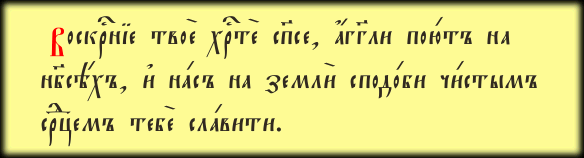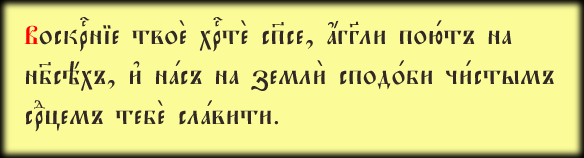
ЦЕРКОВНО-СЛАВЯНСКИЙ ШРИФТ «OSTROG»
Шрифт Ostrog
Гарнитура «Ostrog» — это живое дыхание истории, воссозданное по страницам редчайших изданий второй половины XVI века, выходивших в типографиях Вильно и Острога. Считается, что создателем этого величественного рисунка был сам Петр Мстиславец — выдающийся восточнославянский типограф и верный соратник первопечатника Ивана Фёдорова.
Этот шрифт воплощает в себе строгость и монументальность первопечатных книг, заложивших фундамент всей славянской книжной культуры. Использование гарнитуры «Ostrog» позволяет придать изданию особый статус, подчеркивая глубокую связь времен и верность древним традициям православного просвещения.
Шрифт эпохи первопечатников XVI века. Предположительное авторство Петра Мстиславца.
ЦЕРКОВНО-СЛАВЯНСКИЙ ШРИФТ «POCHAEVSK»
Шрифт Pochaevsk
Гарнитура «Pochaevsk» берет свое начало в богослужебных книгах прошлого столетия, выходивших из стен типографии Почаевской Лавры. За основу современной версии Pochaevsk Ucs была взята исторически точная цифровая копия, сохранившая все характерные особенности лаврского печатного стиля.
В истории создания этого шрифта упоминаются различные исследователи и дизайнеры, вложившие труд в его сохранение: Никита Симонс (1996), архиепископ Иоанн (1999) и представители Orthodox Information Data Associates. Благодаря их усилиям, сегодня мы имеем возможность использовать это наследие для создания текстов, пронизанных духом истинного церковного благочестия.
Историческая гарнитура Почаевской Лавры. Цифровая адаптация мастеров конца XX века.
ЦЕРКОВНО-СЛАВЯНСКИЙ ШРИФТ «POSAD»
Шрифт Posad
Шрифт «Posad» — это еще один выразительный декоративный инструмент, идеально подходящий для художественного оформления заголовков в церковных и исторических изданиях. По своему общему строю и духу он во многом напоминает гарнитуру «Zlatoust», однако обладает своими уникальными чертами, придающими ему особый колорит.
В отличие от более строгого начертания «Zlatoust», буквы «Посада» дополнены характерными засечками и изящными «узелками» на линиях. Эти детали делают рисунок более сложным и насыщенным, отсылая нас к традициям богатого рукописного оформления древнерусских книг, где каждый элемент текста нес на себе печать особого благолепия.
Декоративный заголовочный шрифт с засечками и узловыми элементами.
ЦЕРКОВНО-СЛАВЯНСКИЙ ШРИФТ «PSALTYR»
Шрифт Psaltyr
Шрифт «Psaltyr» — это цифровая адаптация одной из известных дореволюционных печатных гарнитур. Автором исходной компьютерной версии, созданной в 1994 году, является Никита Всесветский. Данный шрифт представляет собой достаточно точную копию своего исторического прообраза, сохраняя дух классического славянского книгопечатания.
При использовании стоит учитывать авторские особенности цифровой версии: буквы здесь вытянуты по вертикали примерно на 20–30% относительно печатного оригинала, а надстрочные знаки расположены более компактно. Несмотря на эти нюансы и некоторые упрощения в рисунке, «Psaltyr» остается востребованным инструментом для тех, кто ищет гармоничное сочетание традиции и цифровых стандартов.
Цифровая версия исторической гарнитуры. Автор — Н. Всесветский (1994).
ЦЕРКОВНО-СЛАВЯНСКИЙ ШРИФТ «SLAVJANIC»
Шрифт Slavjanic
Шрифт «Slavjanic» по своему рисунку близок к известной гарнитуре «Oglavie», однако обладает иными пропорциями и специфической контрастностью линий. Долгое время он оставался практически единственным доступным шрифтом такого типа в кодировке Ucs8, что обеспечило ему широкое распространение в цифровых церковных архивах прошлых лет.
Данная гарнитура выложена прежде всего в целях обеспечения технической совместимости. Мы рекомендуем использовать «Slavjanic» в тех случаях, когда у вас уже имеется готовый текст, сверстанный именно этим шрифтом. Для создания же новых трудов и качественной верстки предпочтительнее обращаться к более совершенной гарнитуре «Oglavie».
Шрифт для совместимости со старыми текстами (Ucs8). Аналог гарнитуры Oglavie.
ЦЕРКОВНО-СЛАВЯНСКИЙ ШРИФТ «STAROUSPENSKAYA»
Шрифт StaroUspenskaya
Гарнитура «StaroUspenskaya» была бережно воссоздана по страницам Псалтири издания Киево-Печерской лавры, предположительно середины XIX века. Она несет в себе те специфичные детали, которые делают узнаваемой любую лаврскую гарнитуру, выделяя её среди прочих богослужебных шрифтов того времени.
Несмотря на свое южное происхождение, рисунок этого шрифта оставляет впечатление удивительной суровости и аскетичной строгости. Его линии вызывают ассоциации с древними северными обителями — морозными Соловками или величественным Валаамом, что делает «Староуспенскую» гарнитуру идеальным выбором для изданий, требующих особого настроя и духовной сосредоточенности.
Киево-Печерская гарнитура XIX века. Характеризуется строгим и суровым рисунком.
Помимо редких литер, данный набор включает в себя символ ударения, что делает его незаменимым инструментом для набора богослужебных текстов, пастырских листков и исторических исследований. Строгие пропорции и классический рисунок знаков обеспечивают безупречную читаемость и создают атмосферу преемственности традиций в каждом печатном слове.